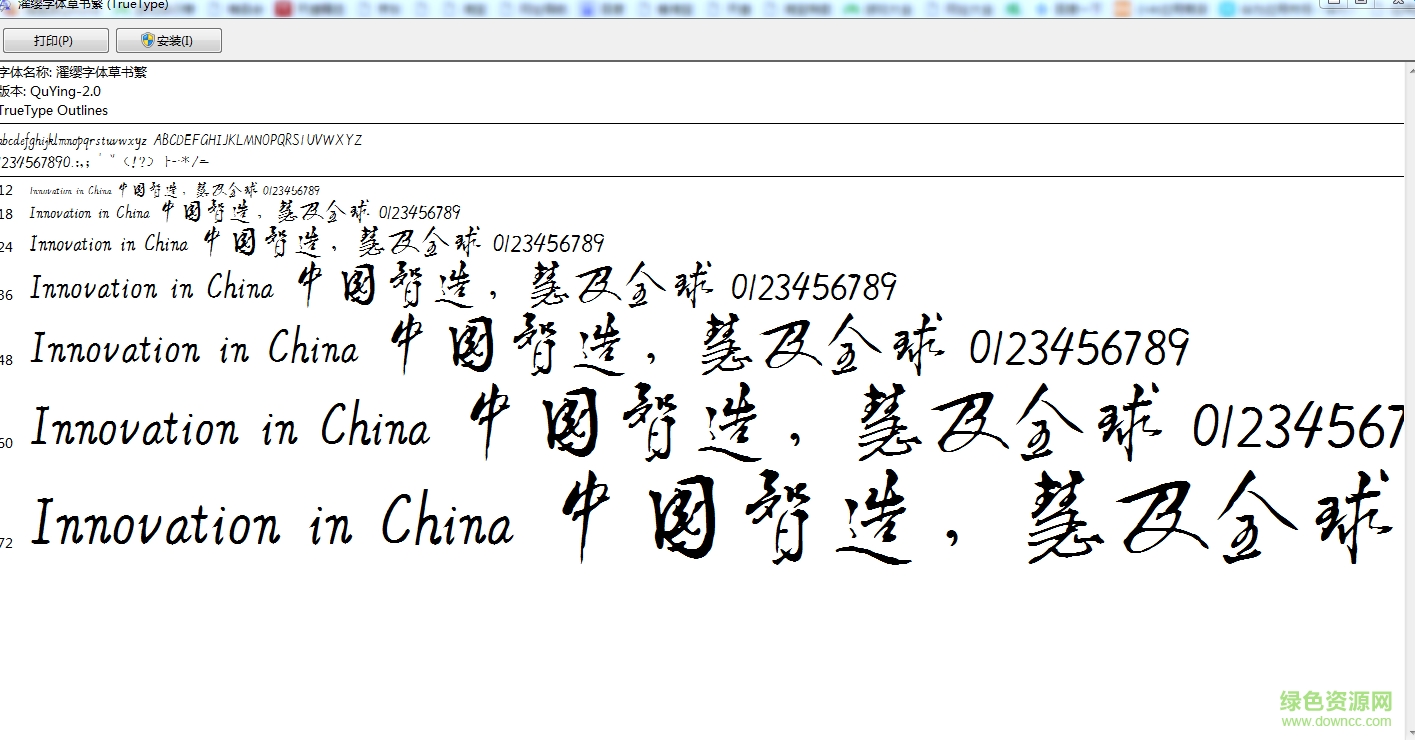
quying 2.0字體又叫濯纓字體草書繁,這是一款用筆奔放的草書字體,線條飛揚,肆意灑脫,結構散而不亂,虛實相生,極具神韻,有需要者快來下載吧!
【今草字體】
今草即一般所說的草書,它是脫去了章草中保留的隸書形跡,并在章草和楷書的基礎上加快行筆,增加圓環(huán)勾連而成。
【狂草字體】
狂草比今草更加簡便快速,且筆勢更加連綿回繞,活潑飛舞,奔騰放縱,大有馳騁不羈,一瀉千里之勢??癫輨?chuàng)始于唐朝,唐人張旭是狂草的開山祖,故有“草圣”之稱。后來的和尚懷素亦是狂草大家。